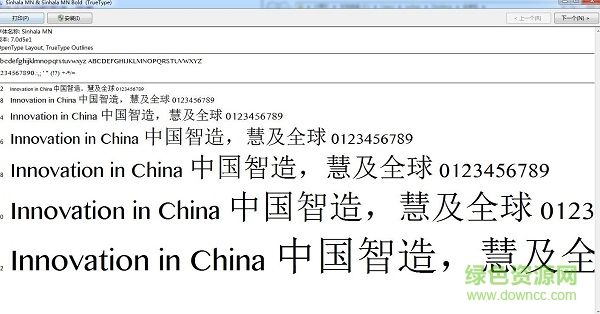
sinhala mn regular
sinhalamn字體是一款常規(guī)襯線字體,該字體線條婉轉(zhuǎn)通暢,動(dòng)靜結(jié)合,方圓兼?zhèn)?,筆畫柔韌但不失力道,適用于各種文藝類型的海報(bào)設(shè)計(jì),需要的朋友快來下載吧!
sinhalamn 常規(guī)